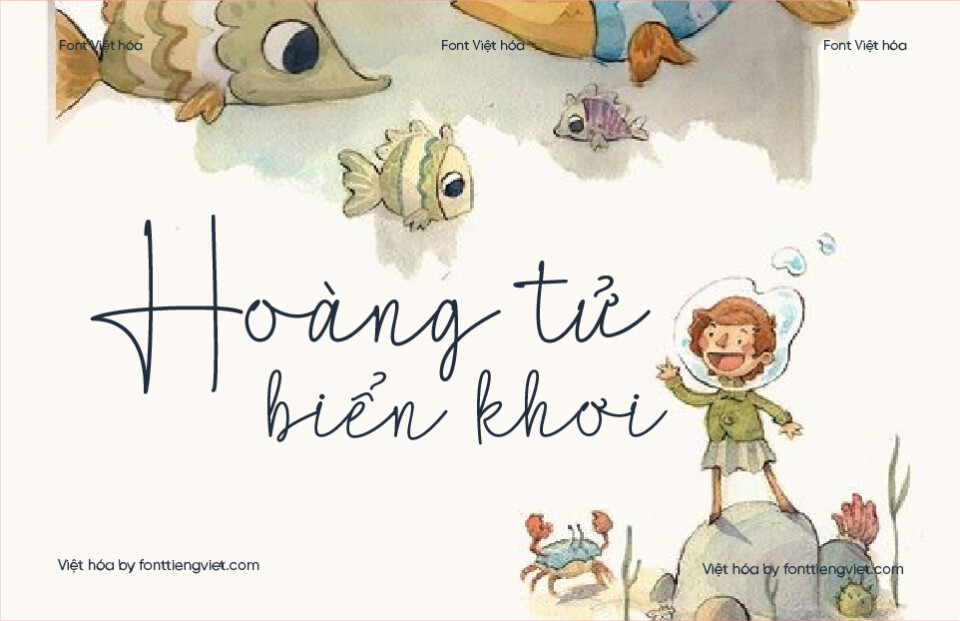
Tải Font Việt hóa 1FTV VIP Love Signature – Nét Chữ Ký Bay Bổng Và Sang Trọng
Giới thiệu về Font Việt hóa 1FTV VIP Love Signature
Trong thế giới thiết kế đồ họa hiện đại, việc tìm kiếm một bộ Font Chữ mang phong cách cá nhân hóa luôn là ưu tiên hàng đầu. Font Việt hóa 1FTV VIP Love Signature là một lựa chọn hoàn hảo dành cho những ai yêu thích sự mềm mại, uyển chuyển của nét chữ viết tay. Bộ font này không chỉ mang lại vẻ đẹp nghệ thuật mà còn được tối ưu hóa hoàn toàn cho tiếng Việt, giúp người dùng dễ dàng sử dụng trên nhiều phần mềm khác nhau mà không lo lỗi hiển thị. Với các đường nét thanh mảnh và bay bổng, 1FTV VIP Love Signature tái hiện chân thực phong cách chữ ký sang trọng, tạo điểm nhấn đặc biệt cho mọi sản phẩm sáng tạo từ học đường đến chuyên nghiệp.
Đặc điểm nổi bật của Font Việt hóa 1FTV VIP Love Signature
Thiết kế tinh tế và chuyên nghiệp
Điểm mạnh nhất của Font Việt hóa 1FTV VIP Love Signature chính là sự kết hợp hài hòa giữa yếu tố thẩm mỹ và tính ứng dụng. Các ký tự được thiết kế với độ nghiêng vừa phải, các nét nối giữa những con chữ tạo cảm giác liền mạch như được viết bằng bút mực cao cấp. Điều này giúp bộ font trở nên cực kỳ phù hợp cho việc làm thiệp mời, thiết kế bìa sách hoặc các dự án nghệ thuật của học sinh, sinh viên.
Khả năng tương thích và ứng dụng đa dạng
Bên cạnh vẻ ngoài bắt mắt, font chữ này còn hỗ trợ đầy đủ các dấu tiếng Việt, đảm bảo tính thẩm mỹ đồng nhất. Bạn có thể sử dụng nó để trang trí bài thuyết trình, làm logo cá nhân hoặc tạo ra những bức ảnh trích dẫn đầy cảm hứng trên mạng xã hội. Sự linh hoạt này giúp font chữ ngày càng được ưa chuộng trong cộng đồng thiết kế tại Việt Nam.
Kết luận về bộ font chữ ký độc đáo
Sở hữu Font Việt hóa 1FTV VIP Love Signature sẽ giúp bạn nâng tầm thẩm mỹ cho mọi dự án cá nhân một cách nhanh chóng. Đây là công cụ đắc lực để thể hiện phong cách riêng biệt và sự chỉn chu trong từng nét chữ. Hãy trải nghiệm ngay bộ Font Miễn Phí, Font Việt Hóa, Font Việt hóa 1FTV VIP Love Signature để cảm nhận sự khác biệt mà nó mang lại cho tác phẩm của bạn.